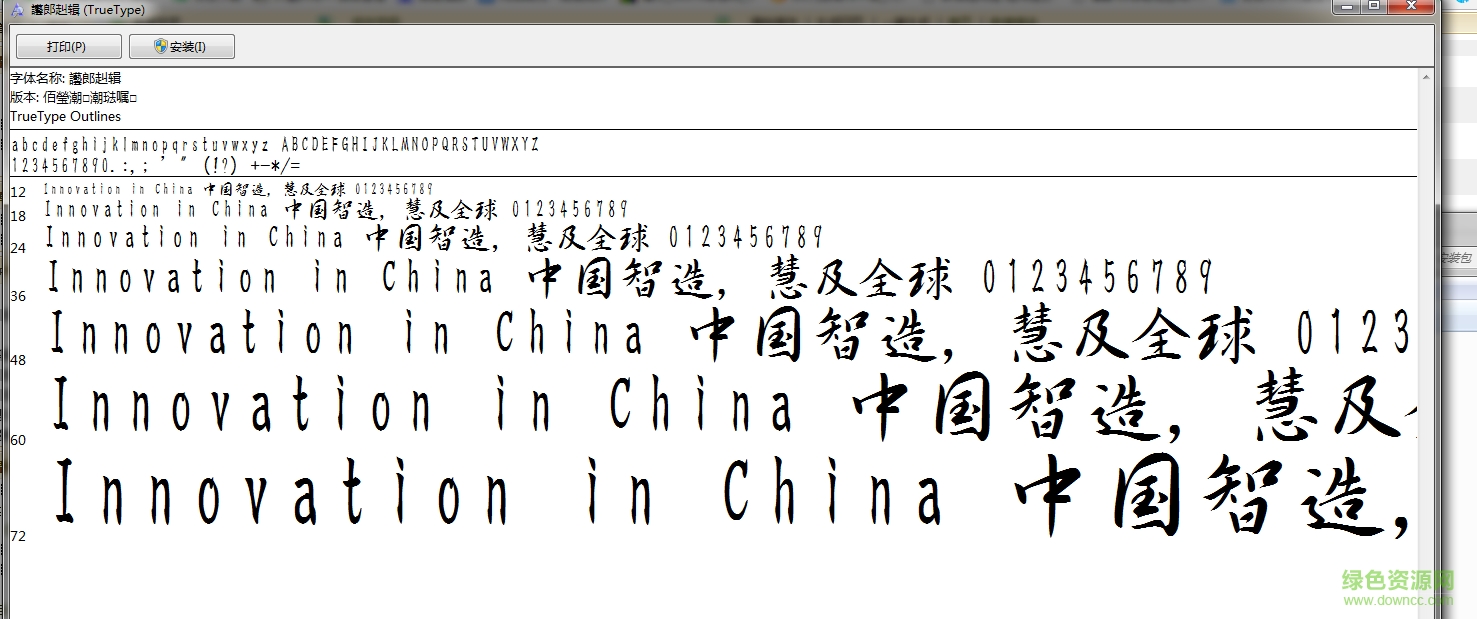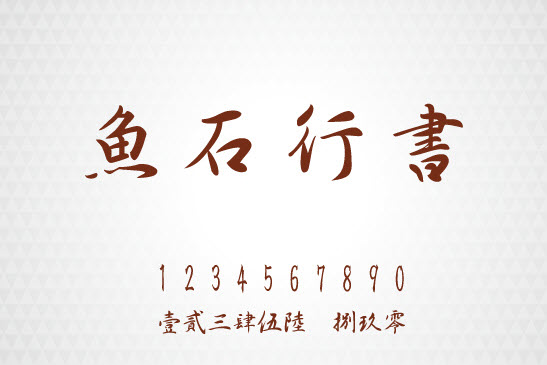
魚石行書字體是一款非常有個性的行書字體,筆法鋒利硬朗,非常的剛勁有力,寫出的中文和繁體字,有一種濃厚的古風氣息,歡迎喜愛的朋友到綠色資源網下載使用!
魚石行書字體是小編一直以來都蠻喜歡一個非常好看的書法字體,話說小學時練毛筆字,初練是可是吃了不少苦頭,不過后來還是很行的哦,咳咳,扯遠了,我們現(xiàn)在推薦這款電腦上使用的字體給大家使用,不過需要注意魚石行書只支持繁體中文哦!